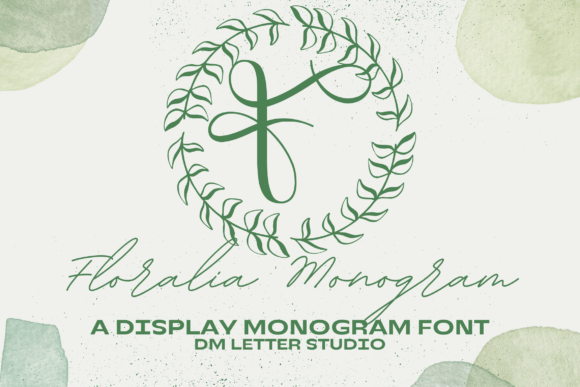
Floralia Monogram
قد يكون العثور على عناصر التصميم المناسبة أمرًا صعبًا، ولكن Floralia Monogram يقدم مجموعة استثنائية ترتقي بعملك على الفور.
سواء كنت تقوم بإنشاء منتجات الطباعة عند الطلب أو دعوات الزفاف أو رسومات وسائل التواصل الاجتماعي، فإن Floralia Monogram هو الخيار المثالي.